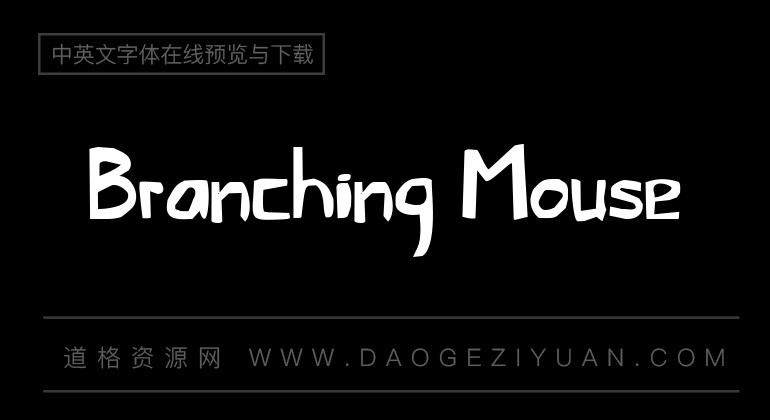
Branching Mouse 字体是一种卡通字体,由著名的设计师Chris Simpson设计。它的特点是有着大胆的曲线和夸张的设计,使得这种字体具有独特的风格。它的特点是字母的外观极其夸张,有着弯曲的曲线和突出的线条,使得这种字体具有较强的视觉冲击力。它可以很好地表达出活泼、新颖和有趣的设计,适用于儿童和游戏类的网站,也可以用于海报、宣传单等设计中。内容介绍
Branching Mouse是一款非常不错的手写艺术字体,具有很好的视觉感,适合于文化类的宣传设计、商业类品牌的广告和产品包装设计以及个性化文字排版等较多场景。